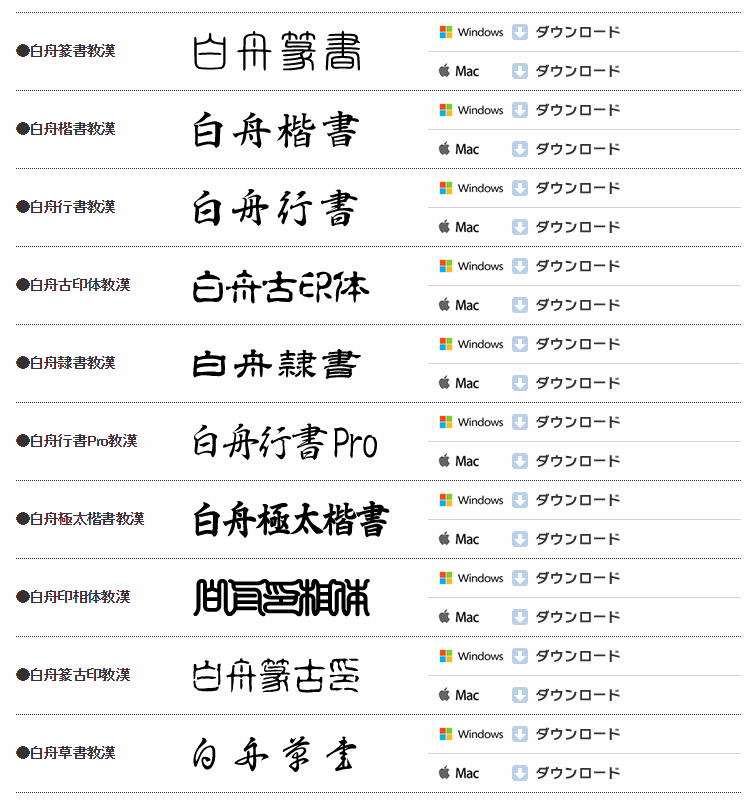
字体介绍
白舟字体是一套设计很漂亮的字体,只可惜这一套白舟书体教育汉字版的汉字数仅1006字(繁体),主要是用于日本小学教育,当中选取使用频率最高的汉字进行。剩下的就是平假名和片假名了。所支持的字可以在本文结尾处查找得到(可以在安装字体之前,先查找一下看看有没有你需要的字)
字体缺失较多,就连数字都没有字形。所以使用这套字体很多时候都要看运气啦,如果刚好有你所需要的文字,那就恭喜你喽!